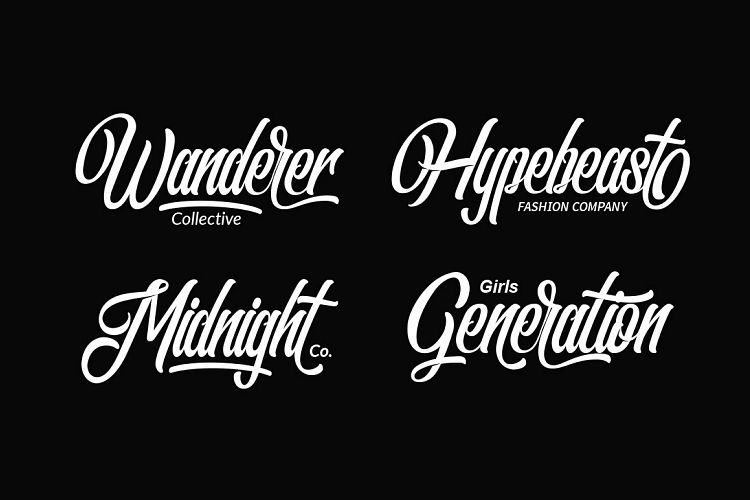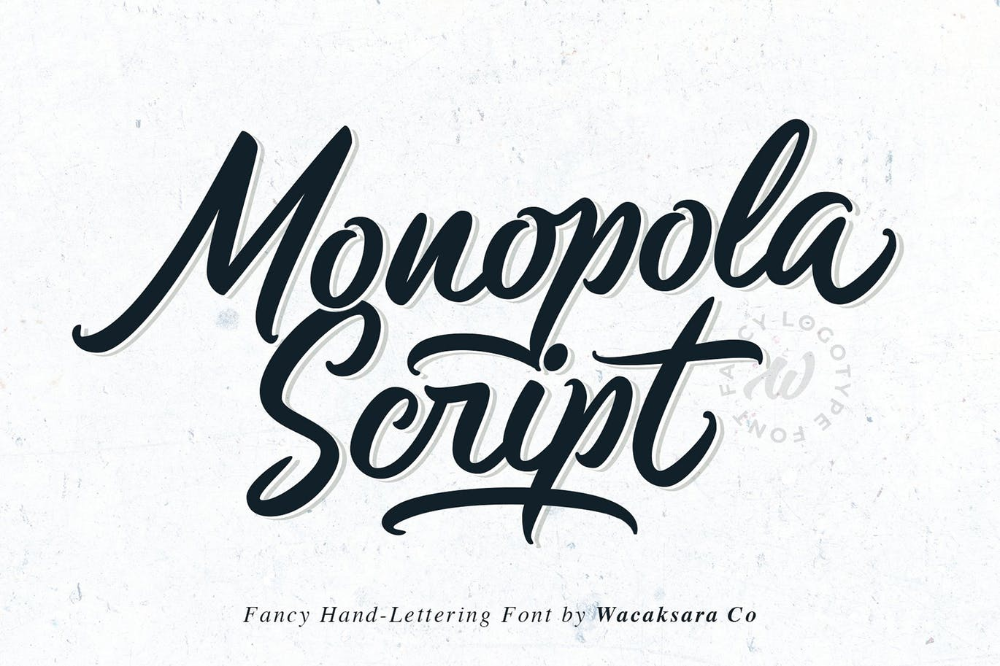
Шрифт жирный рукописный: Рукописные шрифты — русские скачать бесплатно
Более 25 лучших жирных шрифтов, которые будут актуальны в 2022 году
С помощью крупного жирного шрифта названия и заголовки будут обращать на себя внимание издалека.
Вот почему они обычно используются в дизайне плакатов, баннеров и рекламных щитов.
Вам повезло, если вы ищете подобный жирный шрифт для своих проектов. В этой статье мы представим вам его лучшие версии. Вы сможете использовать их для оформления красивых заголовков.
Независимо от того, нужен ли вам шрифт с засечками или без, коллекция, которая представлена в статье, включает все виды жирных шрифтов с современным, винтажным, ретро и рукописным дизайном. К тому же, в наличие есть несколько бесплатных жирных шрифтов.
Трендовый Cred
Cred является прекрасным примером жирного шрифта. Его дизайн отличается объемными буквами, которые будут фантастически смотреться на плакатах и флаерах. Шрифт отлично подходит для проектов в стиле ретро 80-х, а также для урбанистического дизайна.
В наличие также есть набор «ржавых» букв.
Современный Rono
На первый взгляд, шрифт выглядит очень мило. Он поможет вам в формировании эмоциональной связи с аудиторией. Шрифт помимо обычного стиля, включает курсив. В его состав входят как заглавные, так и строчные буквы.
Kust, нарисованный кистью
Этот уникальный шрифт создан вручную профессиональным модельером и художницей Иевой Мезуле. Он включает в себя 80 разных символов, каждый из которых отличается своим неповторимым внешним видом. Дизайн этого шрифта напоминает стиль японского искусства.
Роскошный Goku
Жирные шрифты предназначены не только для создания заголовков, их также можно использовать в дизайне логотипов. Гоку отличный тому пример. Его отличают крупные, элегантные буквы, которые идеально сочетаются с роскошным и высококачественным дизайном логотипов. Шрифт содержит множество лигатур, альтернативных символов и глифов.
Забавный Hit and Run
Этот крупный жирный шрифт отличается веселым дизайном букв.
Он просто идеально подходит для создания заголовков, которые относятся к развлекательной и детской индустрии. Особенно хорошо он будет смотреться на школьных плакатах, баннерах и листовках. Шрифт доступен в формате OpenType.
Бесплатный Hybro
Этот бесплатный шрифт обладает уникальным и смелым дизайном. Он идеально подходит для разработки логотипов, а также для заголовков веб-сайтов и публикаций в социальных сетях. Шрифт полностью бесплатный для использования в личных и коммерческих проектах.
Бесплатный Acier Sans
Если вам нужен жирный шрифт с минималистичным дизайном, этот бесплатный вариант вам подойдет. Его отличают очень крупные буквы. Кроме того, этот шрифт можно бесплатно использовать в коммерческих проектах.
Креативный Blogh
Вы можете использовать этот крупный жирный шрифт, чтобы придать оригинальности дизайну заголовков. Каждая его буква обладает особой индивидуальностью. Шрифт идеально подходит для любых заголовков, начиная от плакатов до видео на YouTube, публикаций в социальных сетях и всего, что находится в этом диапазоне.
Шрифт для названий Fried Day
По одному взгляду на этот шрифт можно понять насколько идеально он будет смотреться на коробке с хлопьями, на плакате, который рекламирует мероприятие для детей, или даже на флаере с информацией о продуктах питания. В его состав входит несколько стилей, включая обычные и контурные версии.
Необычный The Lied
Несмотря на то, что у этого шрифта мультяшный дизайн, на самом деле он отлично смотрится при условии правильного сочетания цвета и фона. Подходящая цветовая палитра придаст оригинальности вашим заголовкам. Или сделайте весь дизайн плаката или флаера более креативным. Шрифт доступен в форматах OTF, TTF и Web Font.
Рисованный Gelly
Gelly — это рисованный крупный шрифт. Он представлен в 2 различных вариантах, обычном и с эффектом пунктира. Его дизайн напоминает каллиграфический стиль. Он лучше всего подходит для создания поздравительных открыток, упаковки, этикеток и т.д.
Футуристический Alectro
Alectro — это уникальный шрифт, в дизайне которого сочетаются современные и ретро-элементы.
Он передает атмосферу футуристического стиля киберпанк. Вы можете использовать его в названиях плакатов, листовок, в заголовках веб-сайтов и многого другого. Шрифт включает в себя заглавные буквы, альтернативные символы, цифры и знаки препинания.
Бесплатный Dujitsu
Вы можете использовать этот бесплатный шрифт в своих личных проектах для создания заголовков и названий. Он будет особенно хорошо смотреться в сочетании с винтажным дизайном, а также вместе с креативными произведениями искусства.
Бесплатный забавный многослойный Thick
Этот забавный шрифт также можно бесплатно использовать в ваших личных проектах. Он выполнен в мультяшном стиле, чтобы придать дизайну заголовка привлекательности.
Комический Thiket
Granbury — современный полужирный шрифт Sans